フォント事情 2015(OS X El Capitan、Typekit)
OS X、Typekitのアップデートでフォント事情が変わってきました。
OS X El Capitanで加わった4フォント
2015年10月1日にリリースされたOS X El Capitanでは、次の4フォントが加わりました(それぞれ2ウエイト)。
- クレー
- 游明朝体+36ポかな
- 筑紫A丸ゴシック
- 筑紫B丸ゴシック
OS X El Capitanで強化されたヒラギノフォント
OS X El Capitanでは、ヒラギノ角ゴシックが10ウエイト(W0からW9)になりました。
OS X El Capitan搭載のヒラギノフォントと製品版のヒラギノフォントには互換性がない
スクリーンからOS X 10.11に搭載のヒラギノフォントと「製品版/従来版フォント(※)」との互換性、使用上の注意点がサイトに掲載されました。
製品版/従来版フォントはありませんので、OS X 10.11の環境のみでご使用ください。
OS X 10.11搭載のヒラギノフォントと製品版/従来版フォントの字形の参考例
OS X 10.11に搭載のヒラギノフォントは、視認性向上を目的として、仮名文字の濁点・半濁点が大きくなっています。そのため、製品版/従来版フォントで作成したデータをOS X 10.11に搭載のヒラギノフォントで開いた場合(またはその逆)、濁点・半濁点のデザインが変わります。また、Adobe InDesign CC/CSや、Illustrator CC/CSなどで、文字間のカーニングを「オプティカル」に設定していると、文字詰めが変化し組体裁が崩れる場合があります。
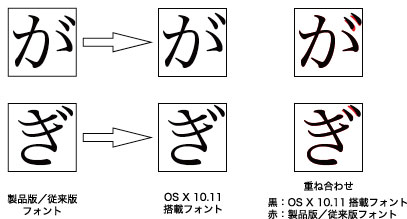
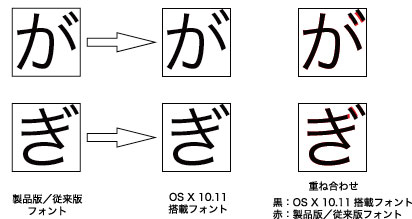
Typekitのアップデートでモリサワ書体10書体(タイプバンク書体10書体)が利用可能に
Typekitには、2015年6月から小塚明朝、小塚ゴシック、源ノ角ゴシック、りょうゴシック、平成角ゴシックなどの日本語フォントが加わっています。
10月5日にアメリカで開催されたAdobe MAXで、なんと!モリサワ書体がTypekitに加わりました。
モリサワ
- A-OTF UD新ゴ Pr6N
- A-OTF UD新丸ゴ Pr6N
- A-OTF UD黎ミン Pr6N
- A-OTF じゅん Pro
- A-OTF リュウミン Pr6N
- A-OTF 中ゴシックBBB Pr6N
- A-OTF 太ゴB101 Pr6N
- A-OTF 太ミンA101 Pr6N
- A-OTF 見出ゴMB31 Pr6N
- A-OTF 見出ミンMA31 Pr6N
Typebank
- RoぶらっしゅStd
- RoサンStd
- Ro日活正楷書体Std
- Ro篠Std
- TBちび丸ゴシックPlusK Pro
- TBカリグラゴシック Std
- TBシネマ丸ゴシック Std
- TB新聞ゴシック Std
- TB新聞明朝 Std TypeBank
- 漢字タイポス415 Std
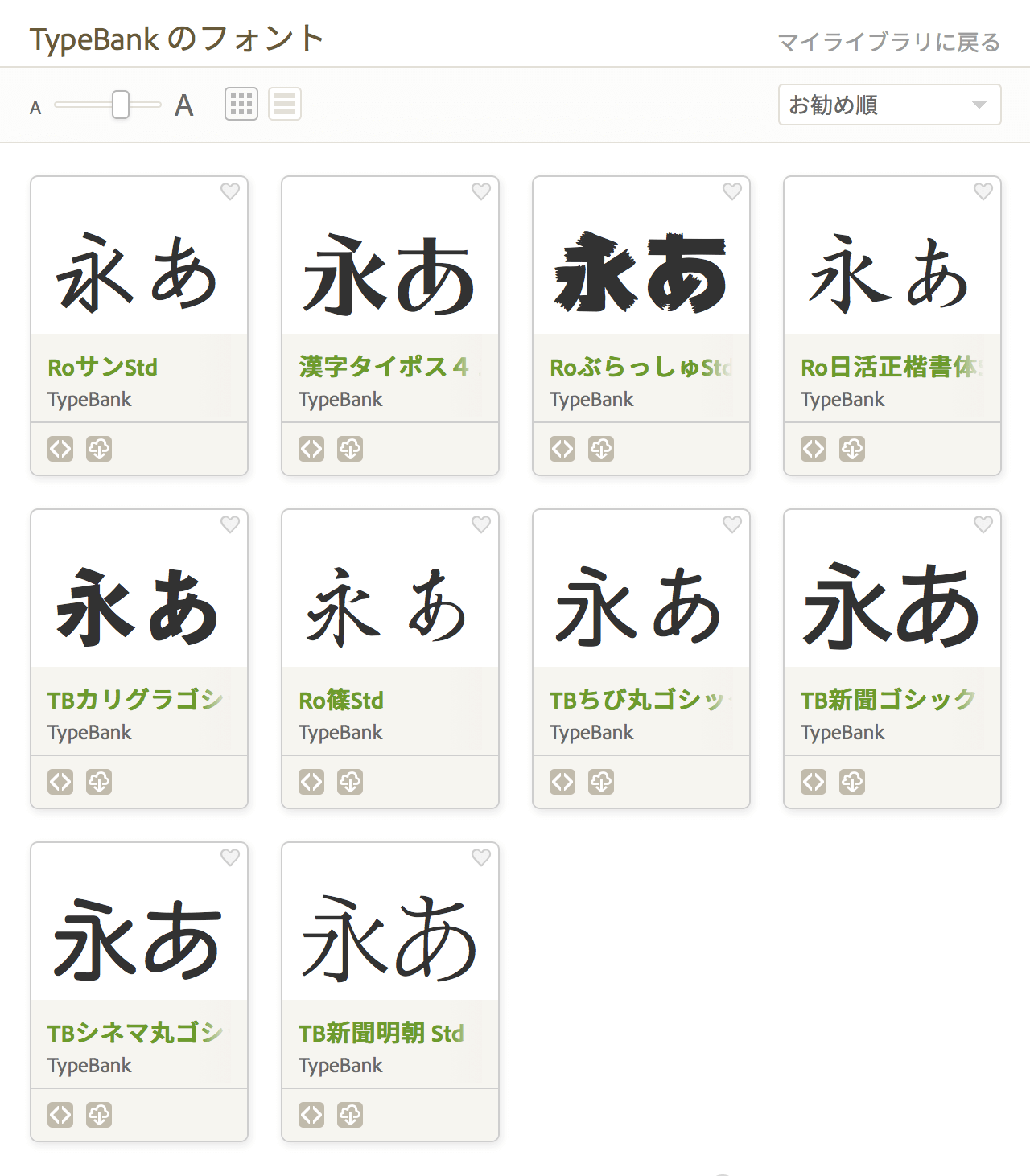
システムフォントの変更
watchOSに続き、OS X El Capitan、iOS 9でもシステムフォントが「San Francisco」になりました。
| OS | フォント |
|---|---|
| OS X El Capitan(10.11) | SF |
| iOS 9 | |
| watchOS | SF Compact |
追記(2015年12月11日):
最も深刻な「異体字テーブルの不具合」は10.11.2で解消。